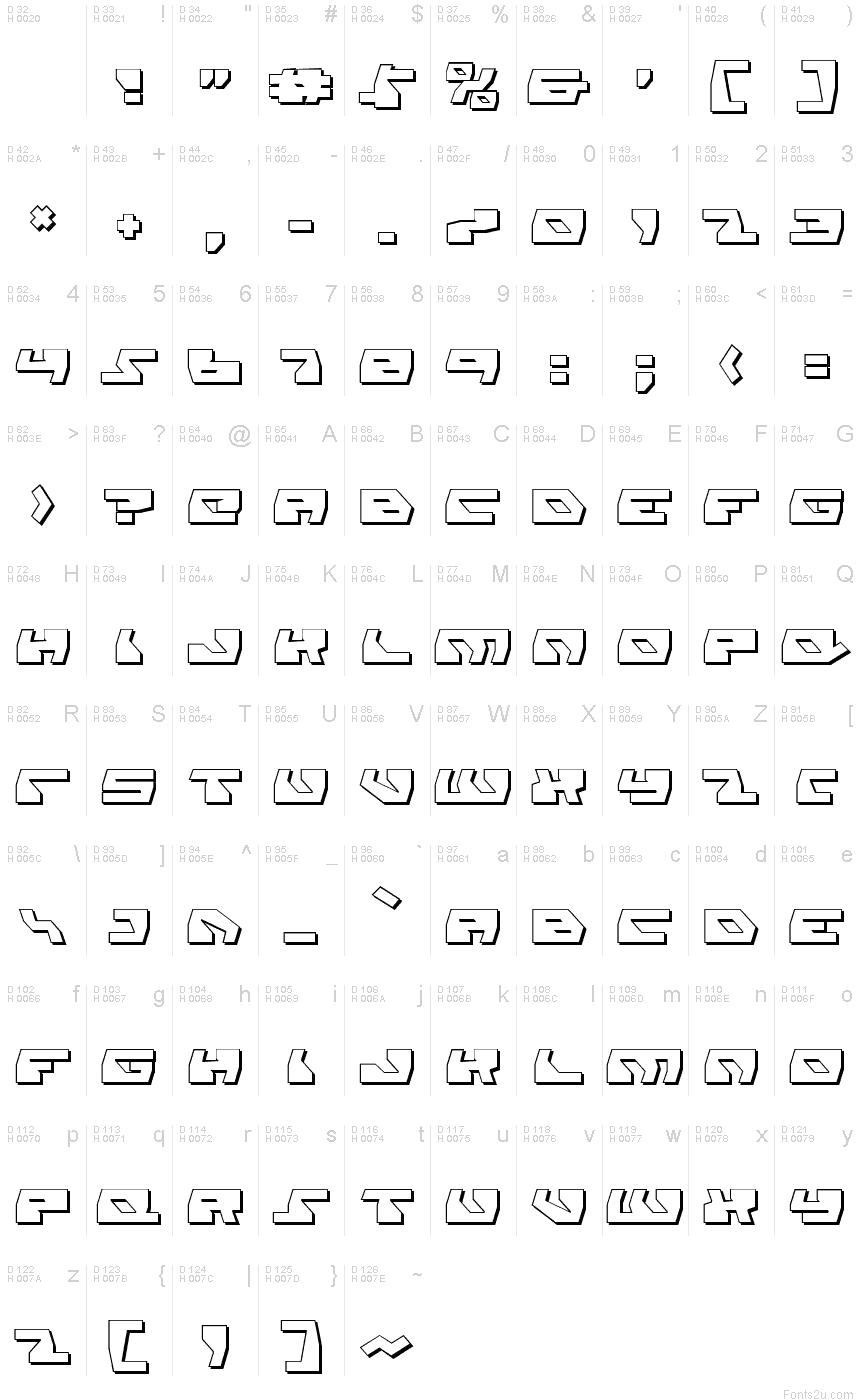
Daedalus Shadow od Iconian Fonts to darmowy krój typu display w technologicznym stylu 3D, z wyraźnym klimatem sci-fi. Wielkie litery zbudowano z masywnych, ściętych form, które nabierają głębi dzięki ostrej, przesuniętej cieniowaniu. Nadaje to literom wygląd wycięty z metalu w estetyce gier arcade, zachowując przy tym ich prosty, blokowy rytm.
Dzięki temu krój ten naturalnie sprawdzi się w logo gier, tytułach na plakatach, okładkach komiksów, nagłówkach na YouTube czy planszach tytułowych, które potrzebują odważnego, futurystycznego wyrazu. Jako darmowy font, najlepiej działa w krótkich, mocnych hasłach, gdzie fasetowane krawędzie i rzucany cień grają główną rolę – zwłaszcza w przypadku monogramów lub pojedynczych słów.
Daedalus Shadow
Dan Zadorozny